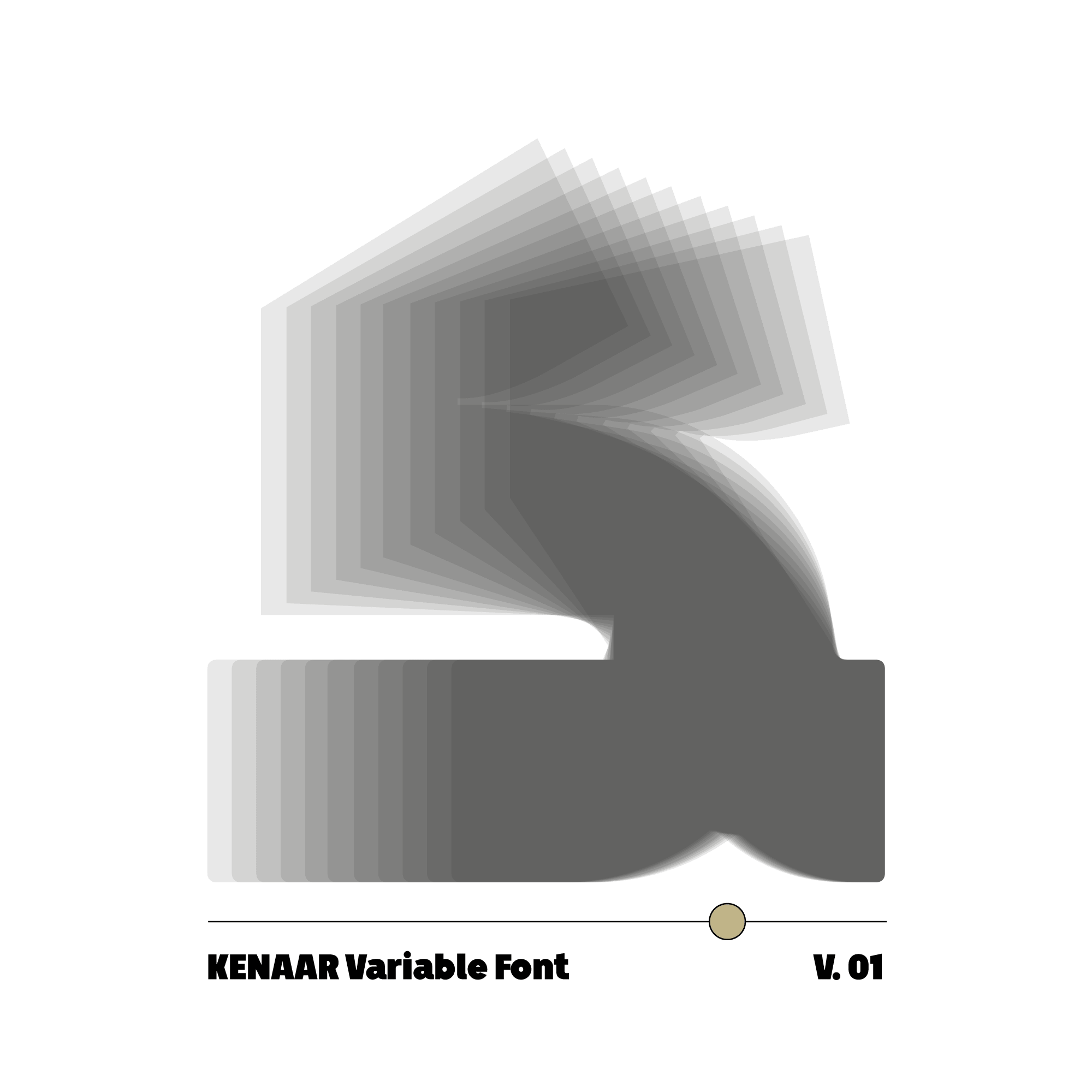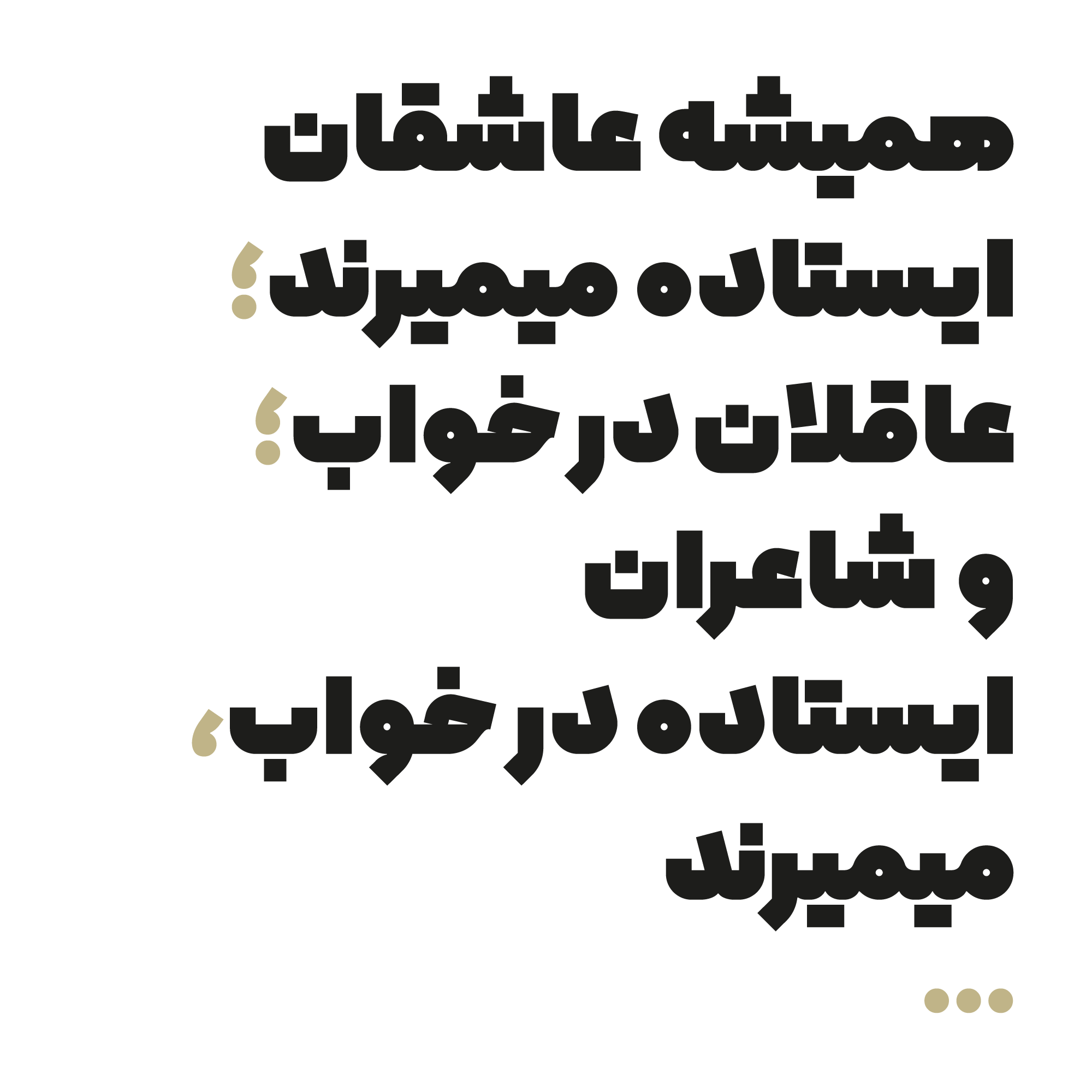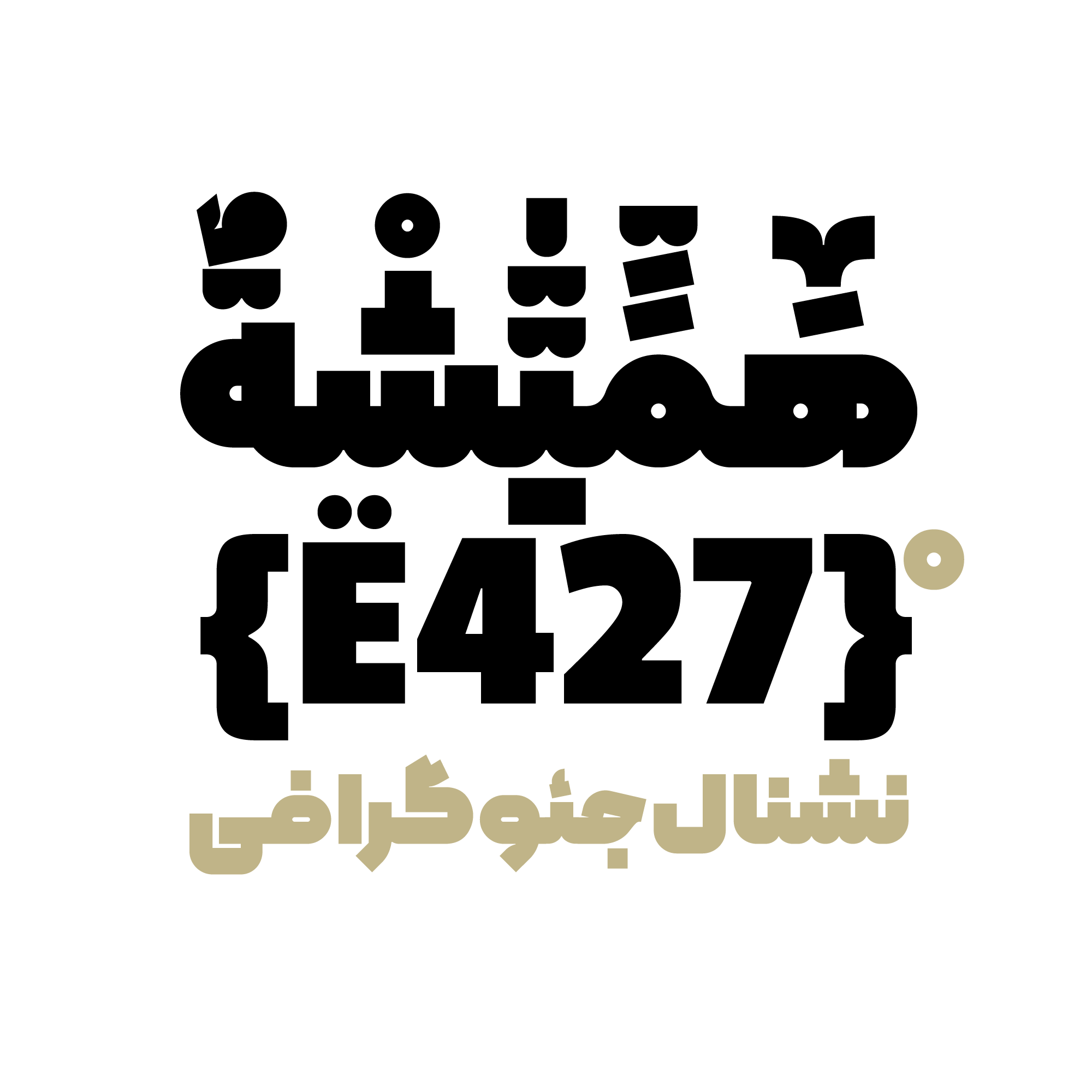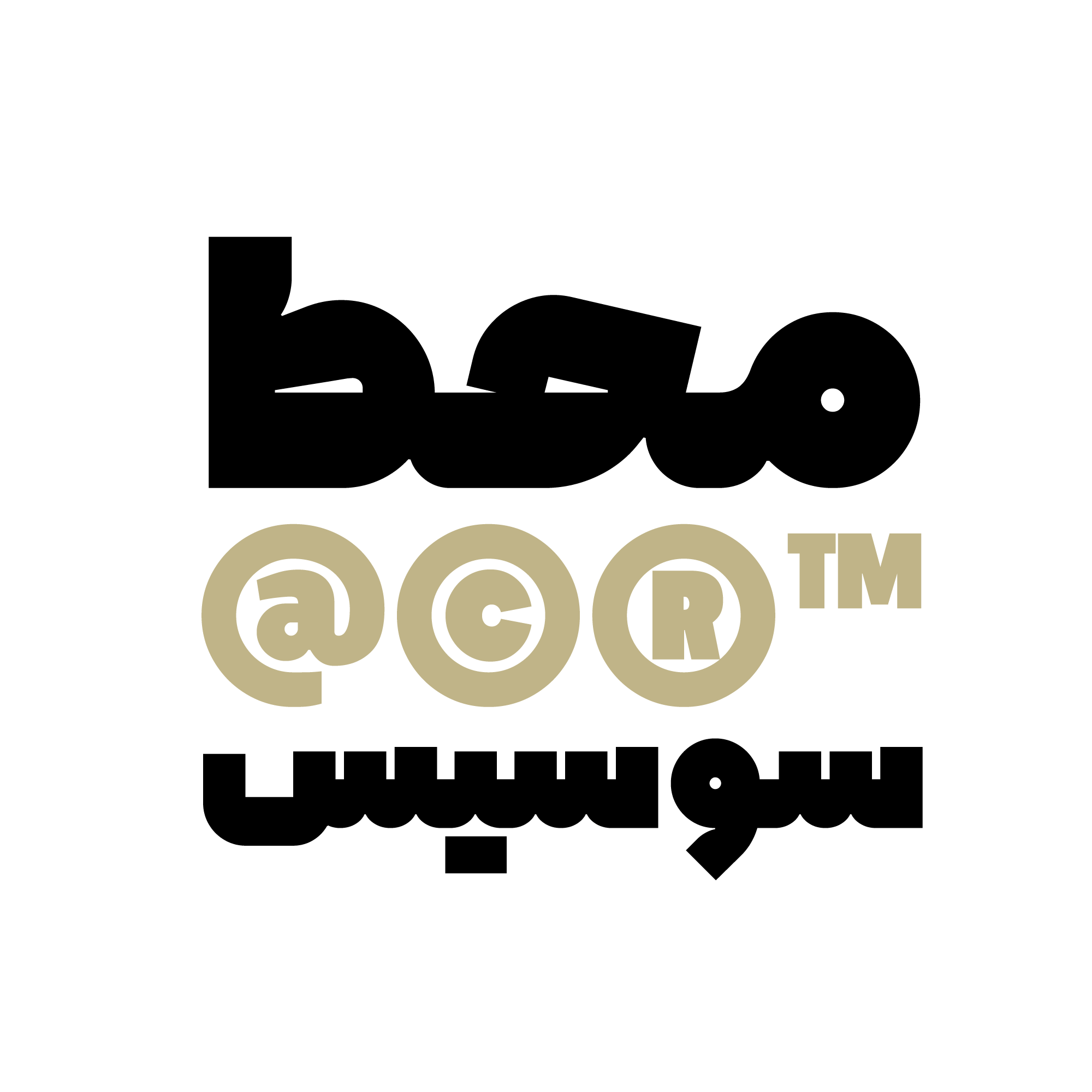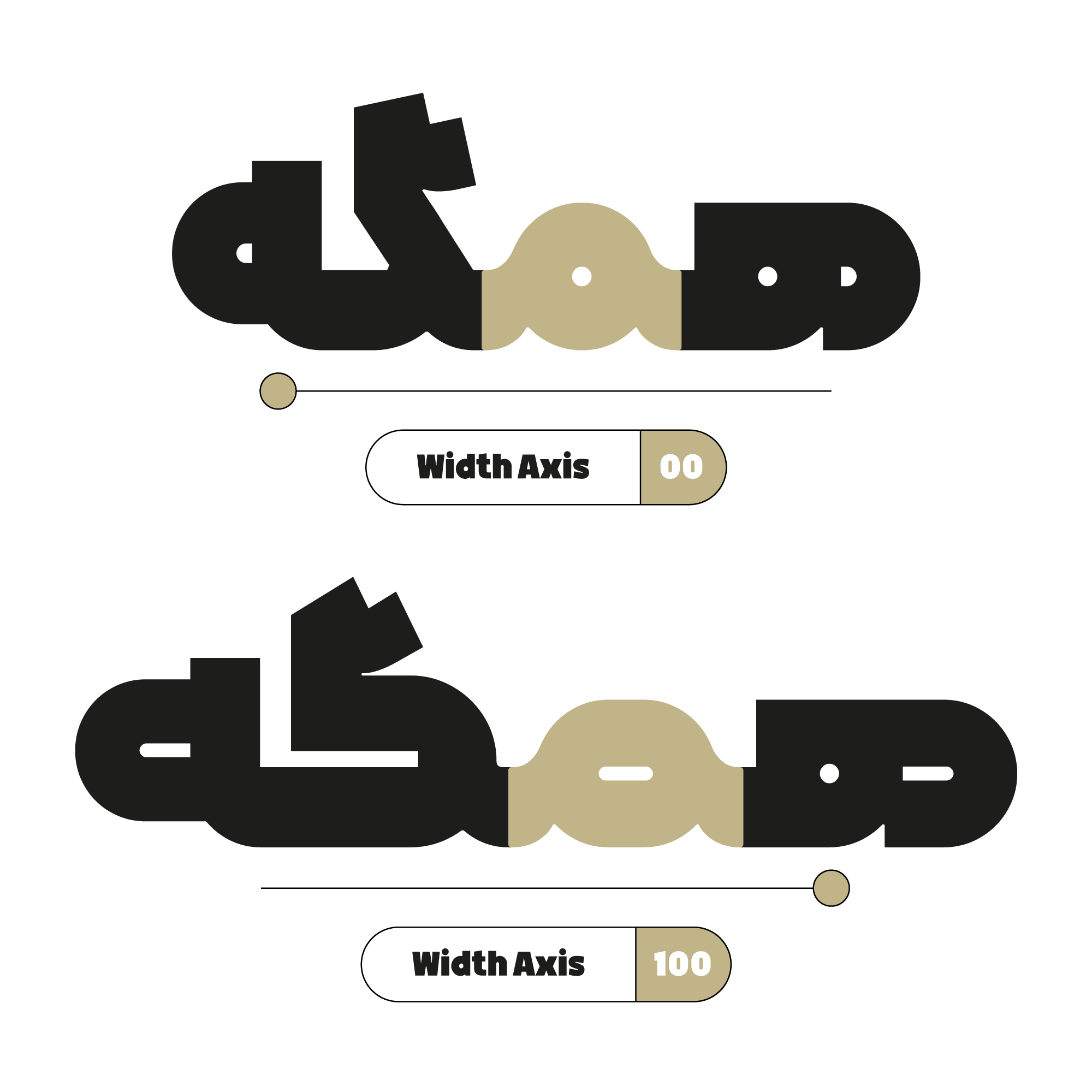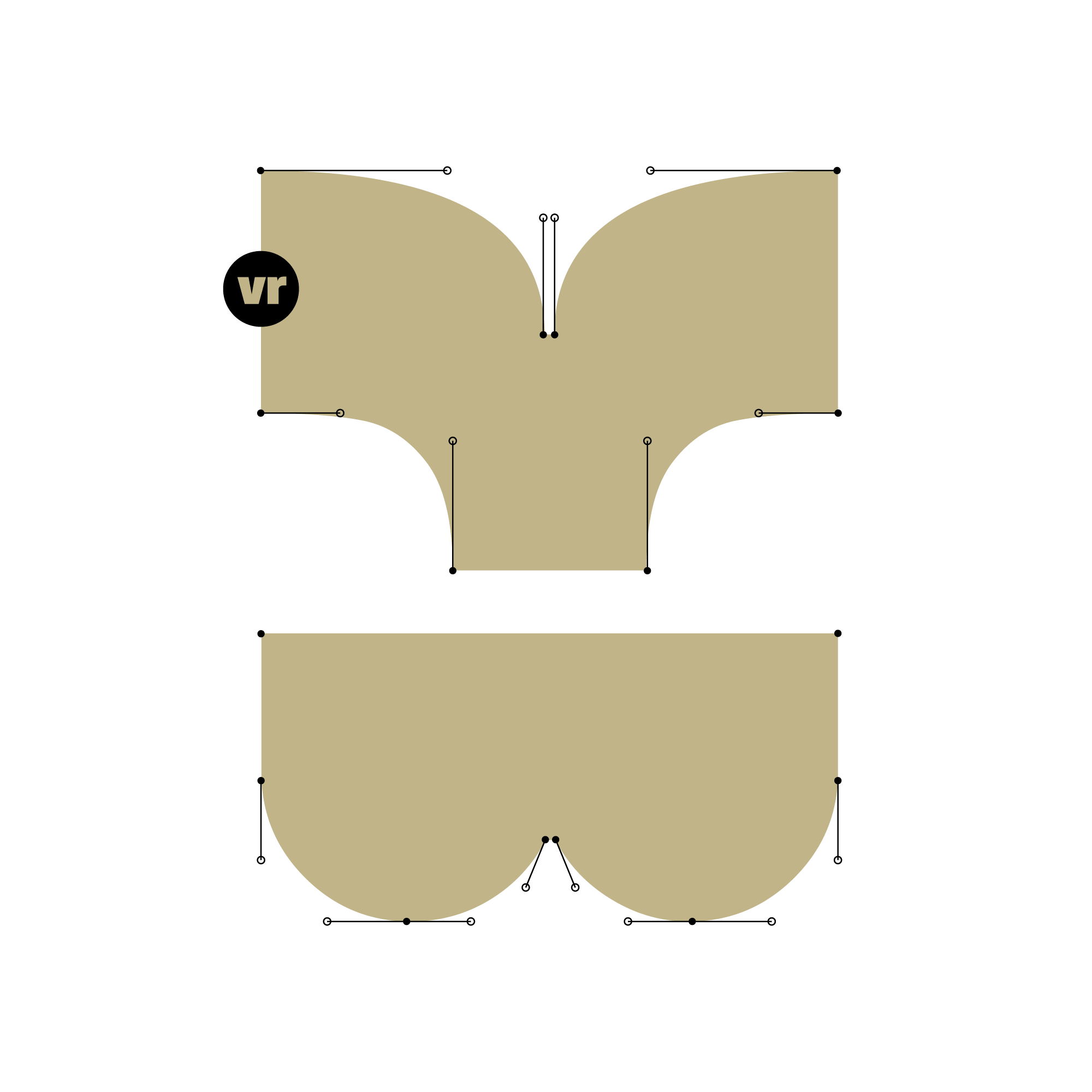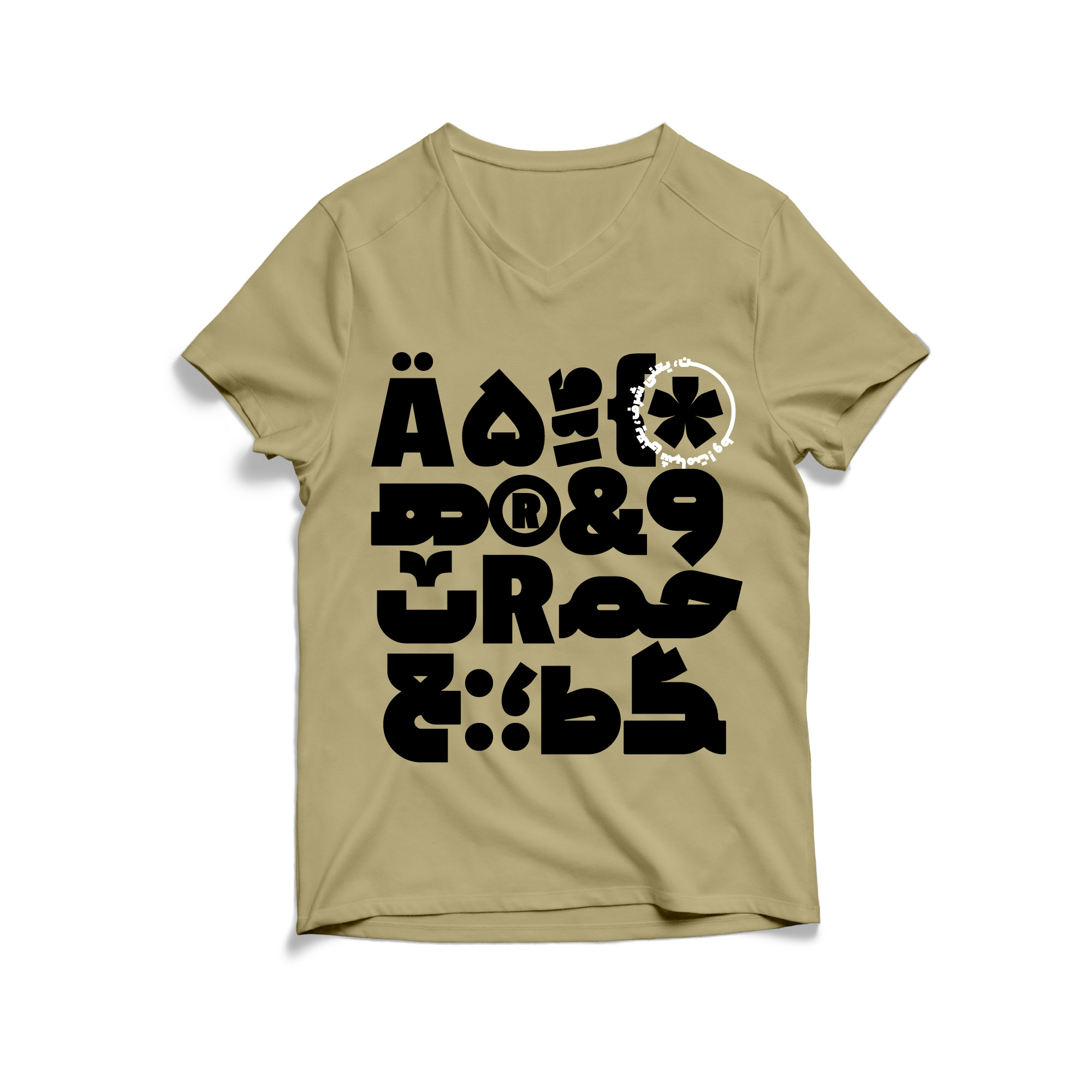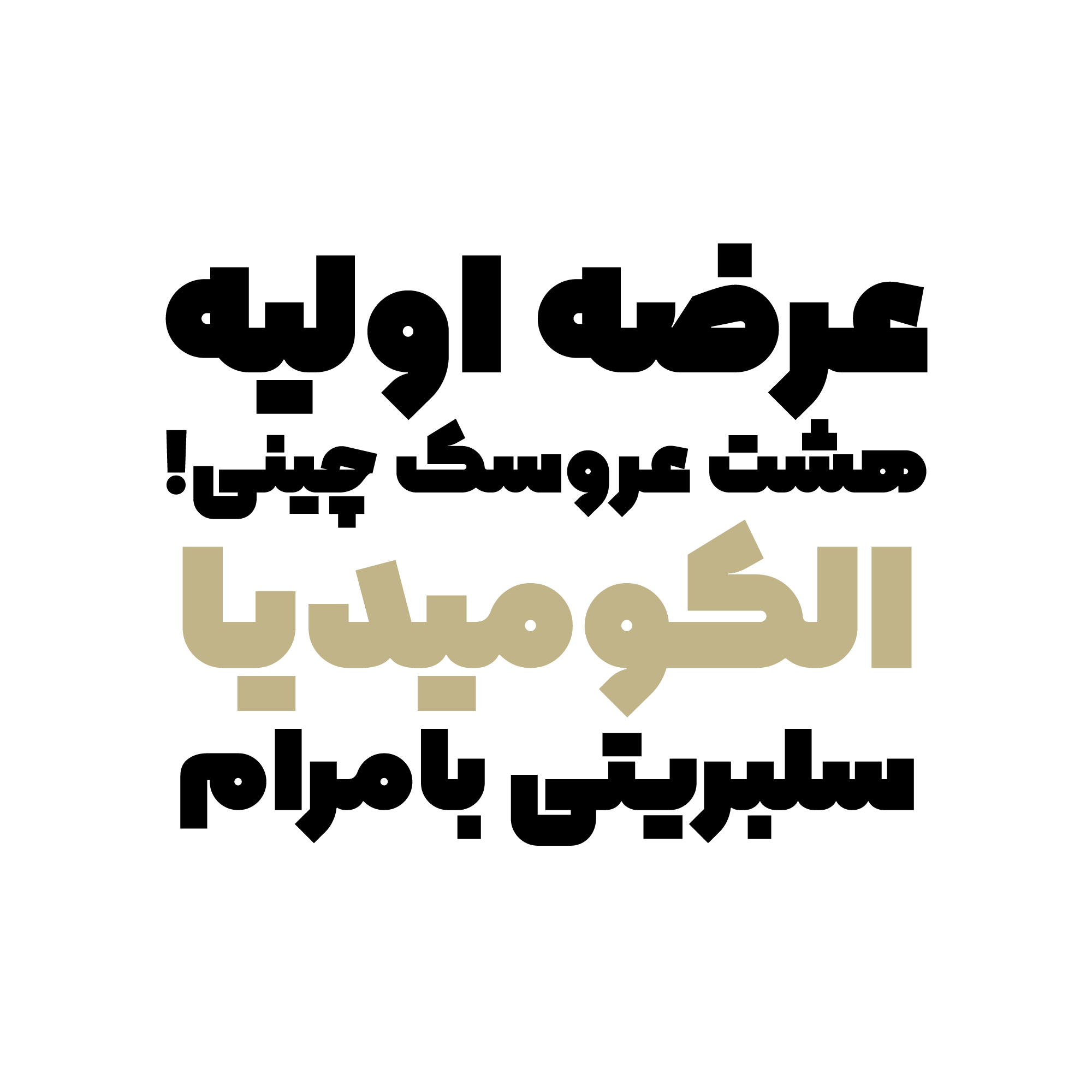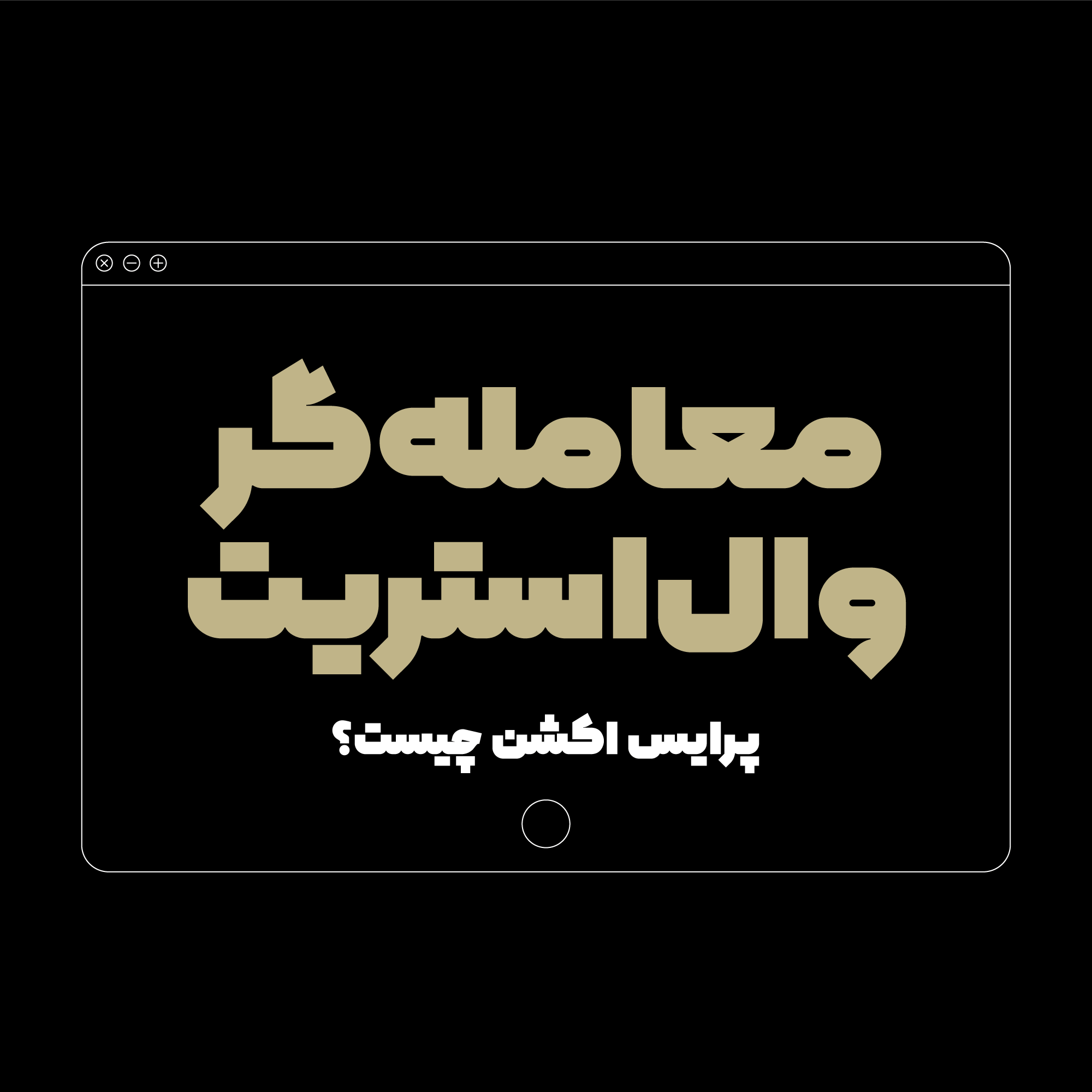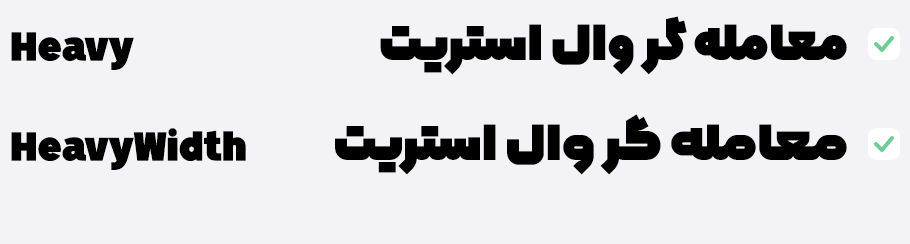
فونتی برای تمام فصول!
تایپفیس کنار برای زبان فارسی، عربی و انگلیسی طراحی شده است و از زبانهای اردو و کردی نیز پشتیبانی میکند. بهدلیل هماهنگی با حروفِ فارسی، برای فونت «کنار» کاراکترهای زبان انگلیسی نیز هماهنگ با حروف فارسی طراحی شده است.
یک heavy واقعی!
فونت کنار دارای تنها یک وزن سنگین است که به شما در نمایش تیترها، عناوین و یا عبارات کلیدی کمک میکند و برای کاربردهای متنوع – از صنعت چاپ تا فضاهای مجازی – درنظر گرفته شده است. «کنار» برای استفاده در فضاهای وب نیز بهینهسازی شده است و فایلهای مورد نیاز در کنار فایلهای اصلی قرار داده شده است.
یک فونت کِشدار!
وریبل فونتِ کنار دارای یک متغیر عرضی است که با آن میتوانید حروف «ک» و «گ» و بعضی از حروفِ چشمدار همانند «م» و «و» را عریض کنید.
هر تیرهای تیره نیست!
مهمترین ویژگیهای بصری فونت کنار پس از هندسی بودن، تیره و پُر بودن آن است. برای کنترل این تیرگی در نقاطی که تلاقی تیرگیها بیش از حد بوده است از inktrap یا جوهرگیر ( فرورفتگی که قابلیت پر شدن داشته باشد ) استفاده شده که از همین روی، میتوان «کنار» را از پیشگامان استفاده از این تکنیک در فونت فارسی به حساب آورد .
حروف جایگزینِ دلبهخواهی!
امان از دست اینستاگرام!
به دلیلِ لحنِ دوگانه ( جدی و شوخی ) و خوانایی قابل قبولِ فونت کنار، کاربردِ آن در محیط رسانههای مجازی همانند اینستاگرام و فیسبوک، و نیز استفاده در بنر تبلغاتیِ سایتها و اپلیکیشنها میتواند به کمک دیزاینرها و توسعهدهندگان وب بیاید.